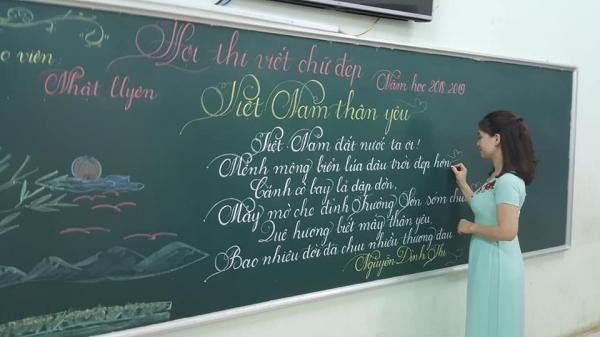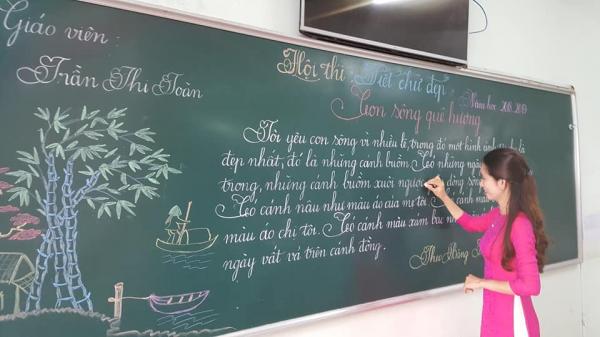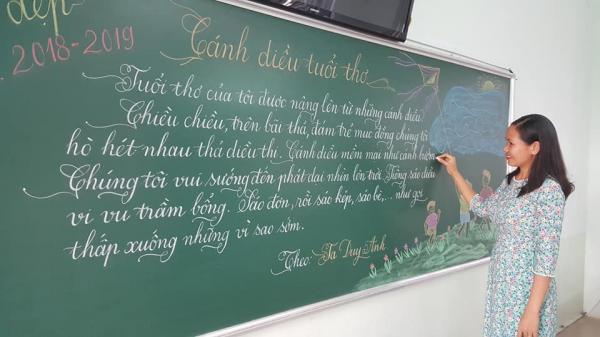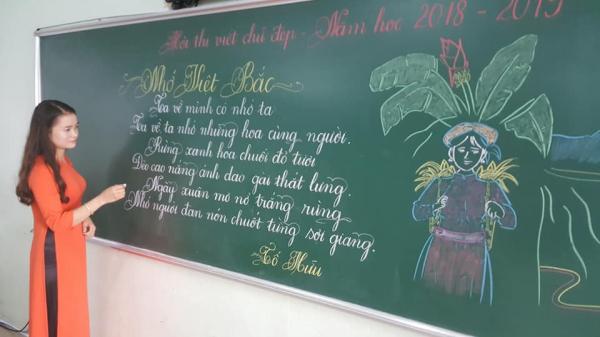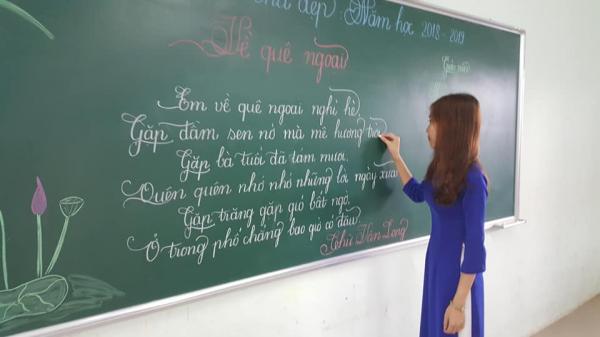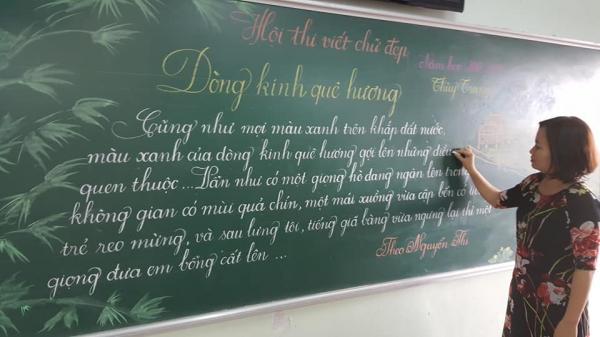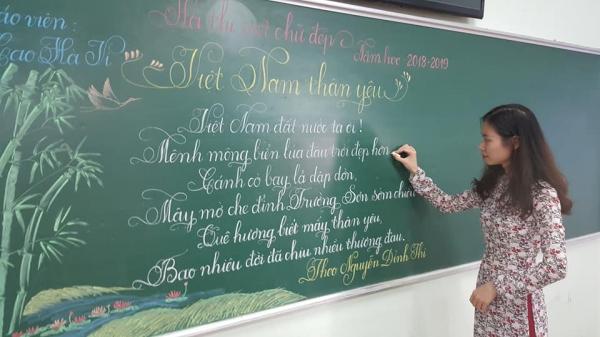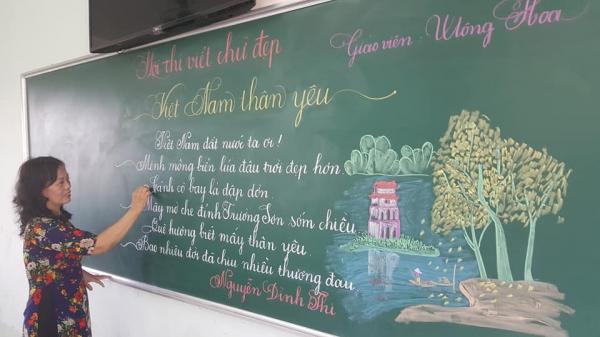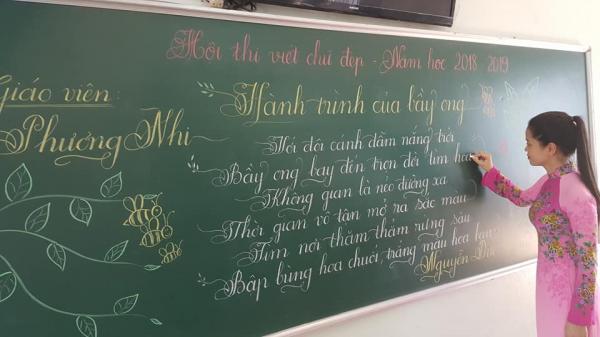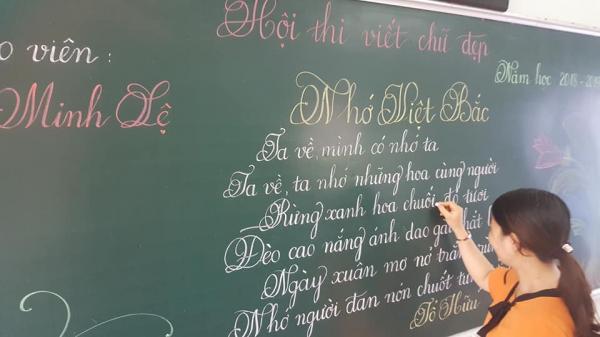
Người xưa có câu “nét chữ, nết người” để giải thích rằng nét chữ không chỉ là cách thể hiện ngôn ngữ của một người mà còn ít nhiều đại diện cho tính cách của người đó. Tuy nhiên, thời buổi công nghệ phát triển nhanh chóng, xã hội bắt đầu không còn quá quan tâm đến nét chữ mà đánh giá ai đó. Nhưng không phải vì vậy mà nét chữ đẹp mất đi giá trị thực sự của nó.
Dù xã hội phát triển ra sao thì khi chúng ta vừa chập chững vào lớp 1, bài học đầu tiên vẫn là rèn chữ và viết chữ sao cho đẹp, cho tròn. Chính vì vậy, giáo viên dạy tiểu học luôn là những người hướng dẫn, làm gương cho các em nhỏ về thói quen viết chữ đẹp, giữ gìn tập vở thật ngăn nắp, gọn gàng.
Mới đây, mạng xã hội rầm rộ chia sẻ về một cuộc thi viết chữ đẹp của các cô giáo tại trường tiểu học Trưng Vương, tỉnh Quảng Trị. Trong bài viết được cô giáo Dung Bùi chia sẻ, cuộc thi có tổng cộng 18 bài dự thi của 18 cô giáo trong trường. Không chỉ thể hiện nét chữ rồng bay, phượng múa, các cô còn tạo ra những bức “tranh chữ” cho tác phẩm dự thi của mình.
Cô giáo Nhật Uyên và bài dự thi của mình. Nét chữ của cô đặc biệt với những chữ cái uốn lượn, mềm mại.
Nét chữ đẹp như in lên bảng.
Cũng dự thi với bài Việt Nam Thân Yêu của tác giả Nguyễn Đình Thi nhưng cô giáo này lại thể hiện những nét chữ với phong cách truyền thống hơn.
Ngoài viết chữ đẹp, các cô còn vẽ thêm tranh minh họa để bài thi của mình trở nên độc đáo.
Trong bài dự thi, các cô sẽ chọn một bài thơ về chủ đề quê hương, đất nước để thể hiện. Mặc dù các bài thi có nét chữ hao hao giống nhau nhưng cũng dễ hiểu, vì đây là nét chữ viết tay rất đặc trưng của nước ta. Nếu nhìn kĩ, bạn sẽ thấy mỗi cô giáo lại có cách lựa chọn nét chữ và tạo điểm nhấn khác biệt đôi chút. Có cô viết thanh mảnh, bay lượn, nhưng cô khác lại chú trọng độ tròn đầy và rõ ràng của mỗi chữ cái. Dù khác hay giống nhau, mỗi bài thi đều là minh chứng cho sự rèn luyện có tâm tư của các cô giáo.
Để thể hiện sự độc đáo riêng, các cô sẽ cho thêm một số chi tiết nhỏ vào mỗi cuối câu hay đầu câu để tạo điểm nhấn.
Bức “tranh chữ” Việt Nam Thân Yêu đáng khâm phục trên bảng đen.
Mỗi cô giáo theo một phong cách chữ viết riêng nhưng nhìn chung đều rất tuyệt vời.
Nếu học sinh được học cùng các cô giáo viết chữ đẹp thì chắc chắn các em cũng sẽ tập được thói quen luôn gọn gàng, ngăn nắp.
Ngay sau khi xuất hiện trên mạng xã hội, những hình ảnh này đã trở thành cơn sốt trên khắp các nhóm thảo luận lớn nhỏ trên Facebook. Những bức “tranh chữ” này đã ngay lập tức nhận được hàng nghìn lượt tương tác chỉ sau vài giờ đăng tải.
Không có bất cứ font chữ máy móc nào sánh bằng nét chữ viết tay siêu đẹp này.
Ai cũng viết đẹp, giám khảo chắc sẽ khó chọn lắm đây.
Bạn đoán ai sẽ là quán quân của cuộc thi này?
Cuộc thi có sự tham gia của tất cả các giáo viên chủ nhiệm ở trường. Trường học gì mà các cô giáo ai cũng viết chữ đẹp.
Nhiều người hoài nghi về sự thật trường tiểu học có đội ngũ giáo viên ai cũng viết chữ đẹp. Nhưng nếu nhìn kĩ, bạn sẽ thấy mỗi nét chữ đều khác nhau và rất riêng biệt.
Nếu những nét chữ này viết trên giấy chắc chắn sẽ có nhiều người tưởng lầm đây là chữ in.
Những bức tranh quê hương cũng được các cô giáo vẽ rất đẹp.
Lần đầu tiên biết được một cuộc thi mà tất cả thí sinh đều ngang tài ngang sức.
Để có nét chữ đẹp, chắc chắn các cô đã bỏ ra rất nhiều thời gian để luyện tập.
18 tác phẩm tuyệt đẹp bất phân thắng bại!
Nhiều bình luận cũng thể hiện sự khâm phục của mình đối với nét chữ xinh đẹp như in lên bảng của các cô giáo. Nhờ đó, ngôi trường tiểu học Trưng Vương cũng được thơm lây khi bài đăng mỗi ngày một nhận được nhiều sự quan tâm hơn. Chắc chắn chẳng có font chữ máy móc nào có thể sánh được với sự tận tâm và rèn luyện khổ nhọc của những người đưa đò cho thế hệ tương lai.